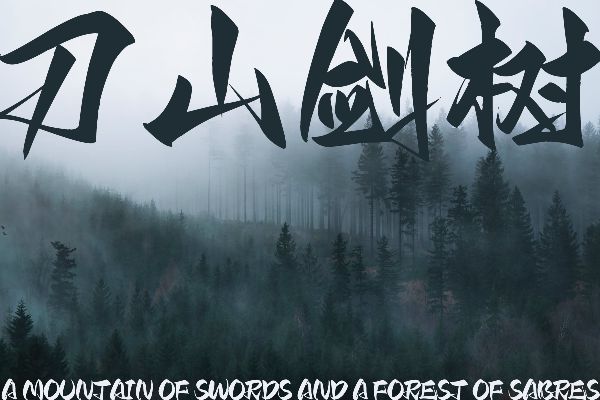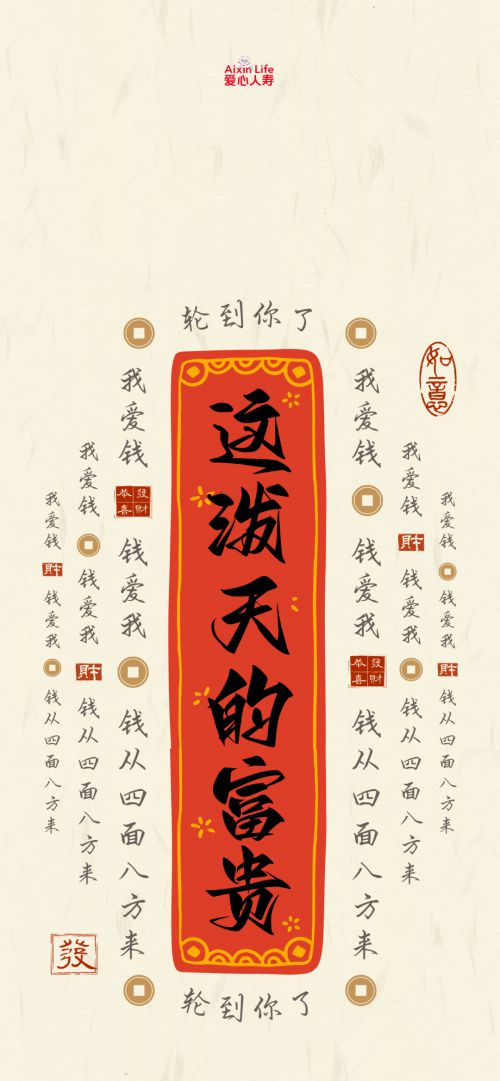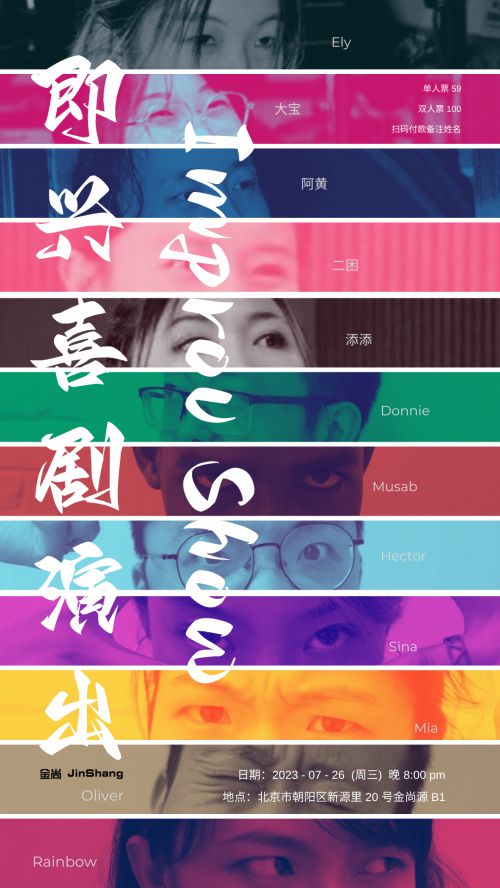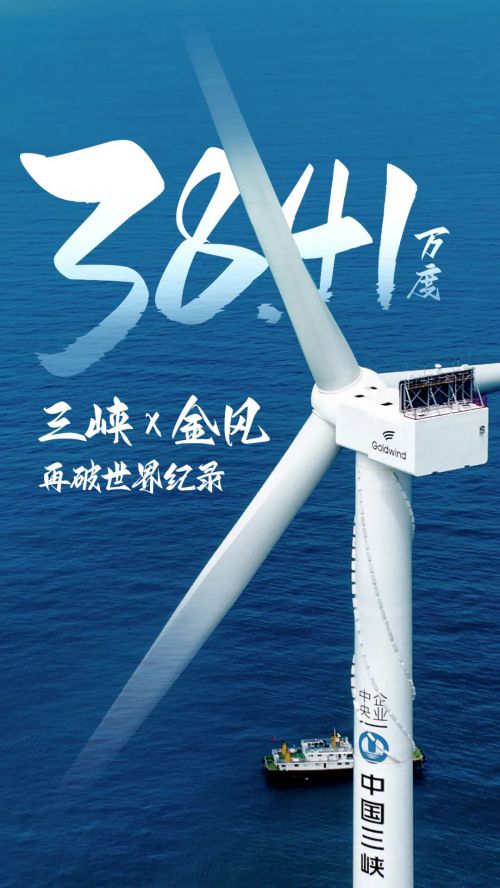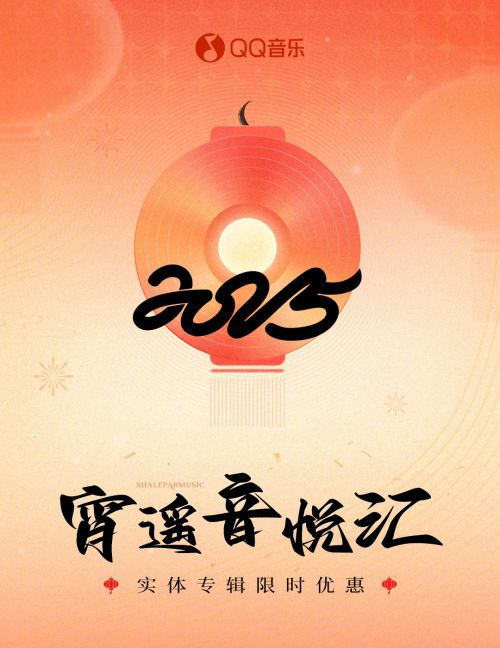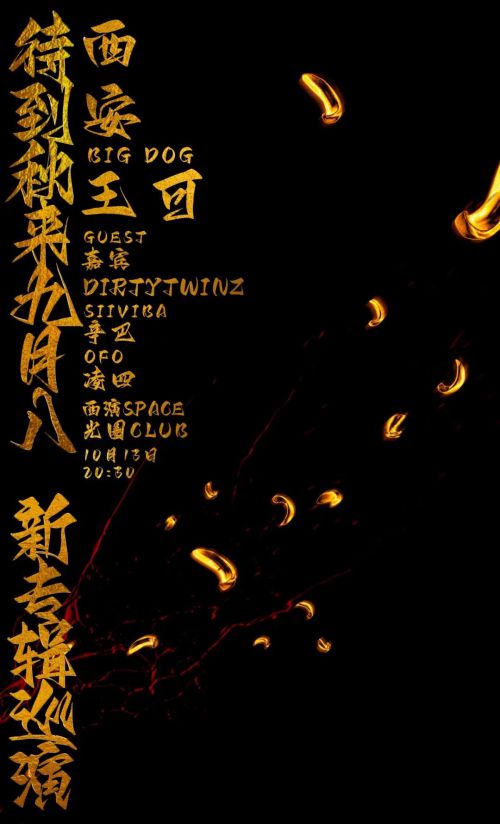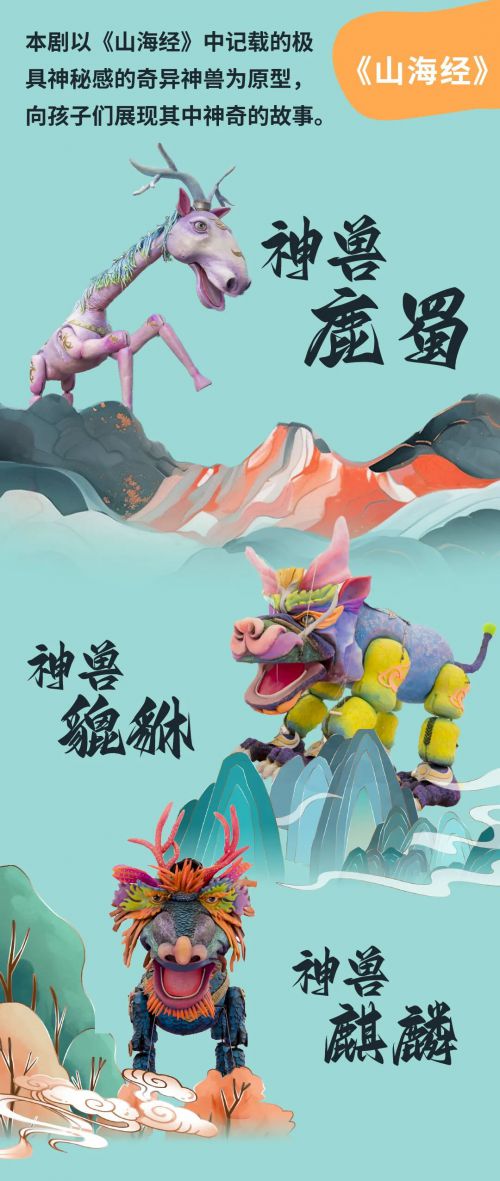
Aa剑豪体
剑豪体是Aa字库推出的一款中国风手写体,以“力量”与“豪放”为核心气质,将传统书法韵味与现代设计需求巧妙融合。作为免费商用字体,剑豪体凭借独特的字形设计,成为文化创意领域的实用之选。 剑豪体字形修长劲挺,重心巧妙上移,中宫收紧的结构让字体在紧凑中透出张力,宛如剑刃出鞘般利落。笔型融入利落斜切,搭配方头笔画收尾,锋芒暗藏却不失沉稳;笔画粗重均匀,断连分明的处理既保留手写的随性,又透出剑势般的刚劲——每一笔都似运力挥毫,将“侠气”与“力量”具象化。 无论是武侠主题海报、古风文创设计,还是个性标题创作,剑豪体都能以其中国风手写特质,传递豪迈洒脱的东方韵味。免费商用的授权优势,更让创作者无需顾虑版权,轻松用笔墨“剑影”打造兼具视觉冲击与文化底蕴的作品。